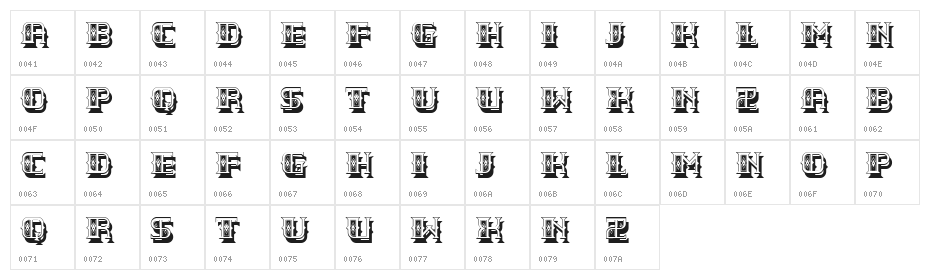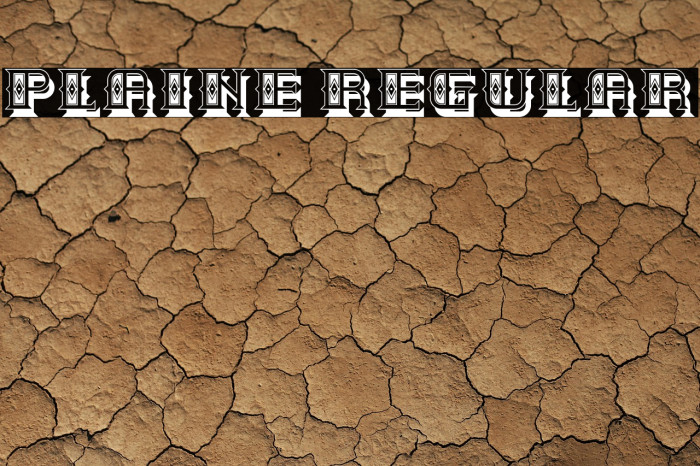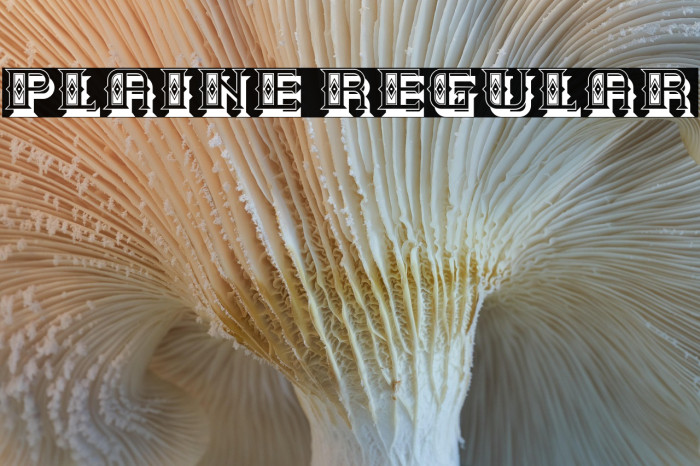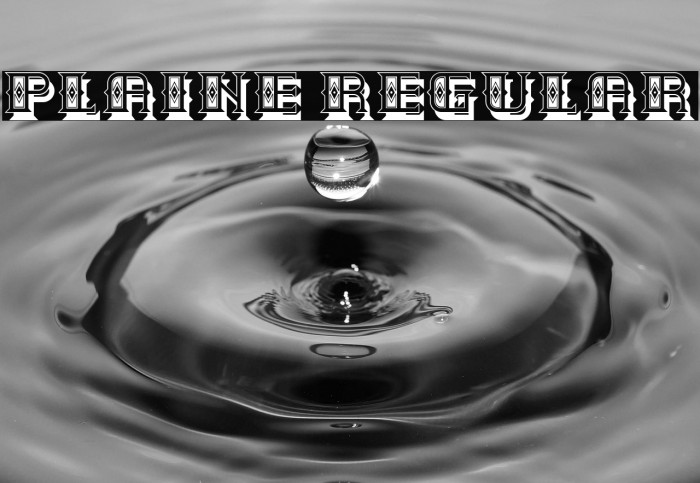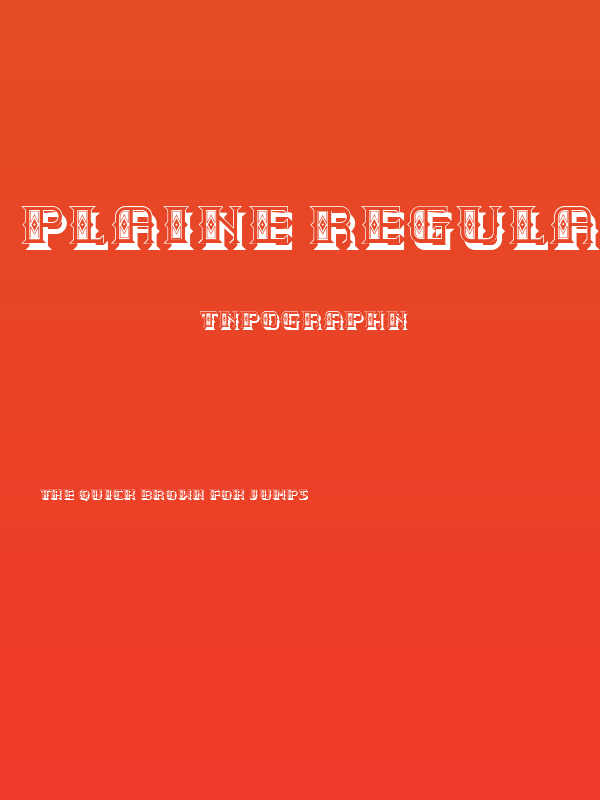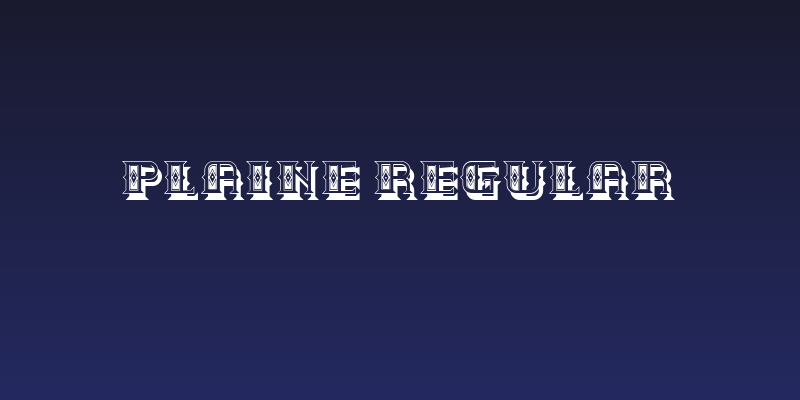
Plaine Regular Font
| Categorie | Gothic |
| Stile generale | Vintage, Decorative |
| Progetti proposti | Ideal for poster designs, album covers, branding for vintage-themed events, or any project needing a dramatic and artistic touch. |